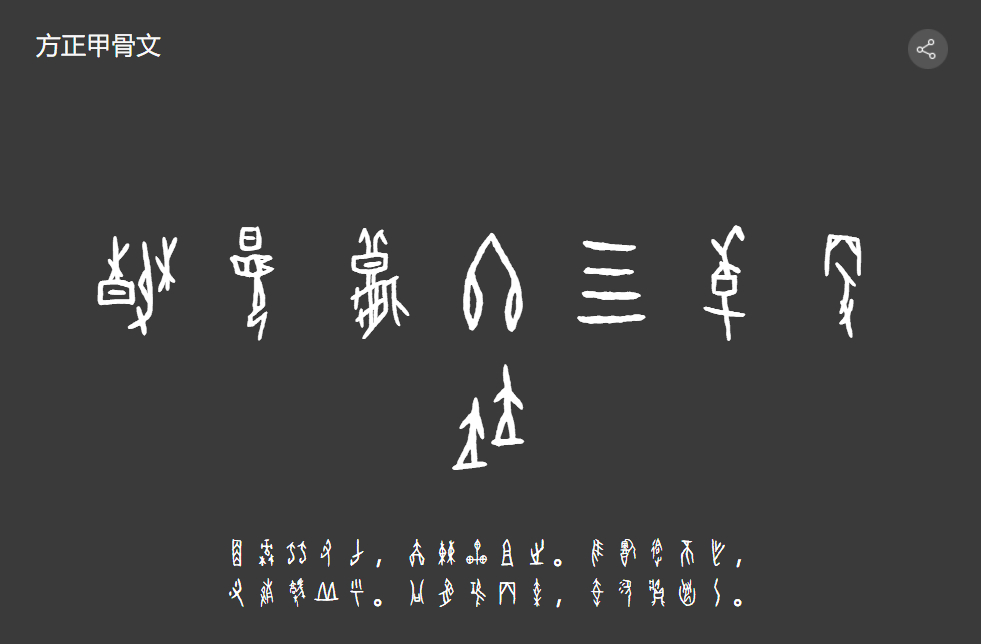
关于甲骨文:甲骨文,指刻写在龟甲、兽骨上的文字。主要发现于河南安阳小屯村一带的殷墟,是商代后期王室和贵族用于占卜和记事的文书,又称契文、甲骨刻辞、卜辞等。所发现的殷墟带字甲骨的数量已有16万片之多,是目前已知中国最早的成体系的文字,主要记载了殷商社会的历史和文化。从甲骨文发现到现在已逾一百二十余年,甲骨文的国际影响力和文化意义日益彰显。
字体特征:甲骨文字库收录字形均在相对公认的已释读的甲骨文范围之内;字形主要以殷墟卜辞原拓和部分周代甲骨文为基础;以典型宾组类为主要字体风格;其字形结体对称而稳定,其线条遒劲坚实、挺拔爽利,曲直粗细均备,笔画多方折。甲骨文字库还原了文字的象形,生动而有趣,又充满了历史的厚重感。
设计师:陈宇